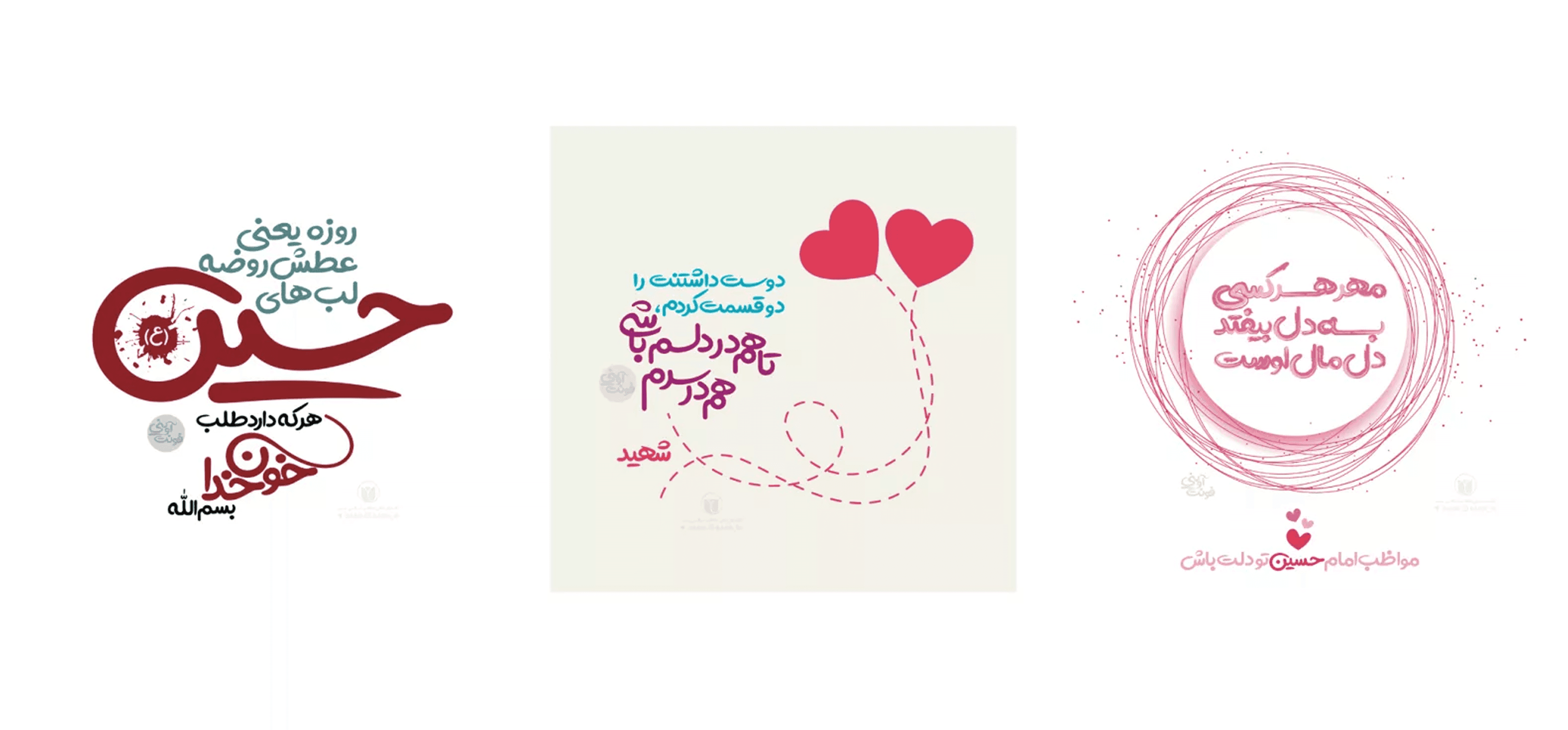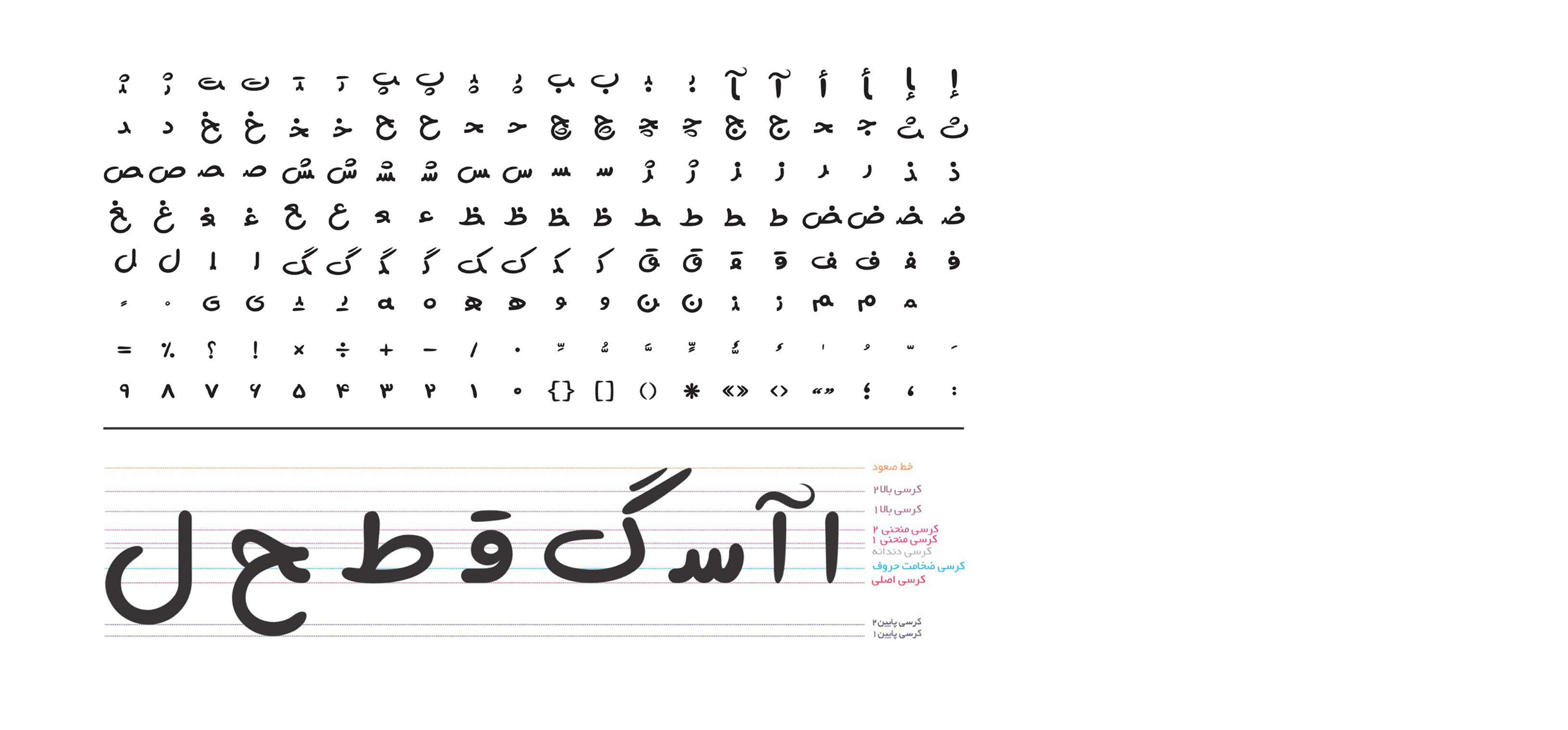
"آوینی" هو خط يدوي فانتزي يتميّز بأسلوب كتابة انسيابي وحيوي.
في تنفيذ هذا الخط برمجيًا، تم الحرص قدر الإمكان على جعل أشكال الحروف ناعمة وخالية من الزوايا الحادة أو التكسرات، ونتيجة لذلك، تواجه خطًا جميلًا ينقل بسهولة إحساسًا بالبهجة والحيوية إلى تصميمك الجرافيكي.